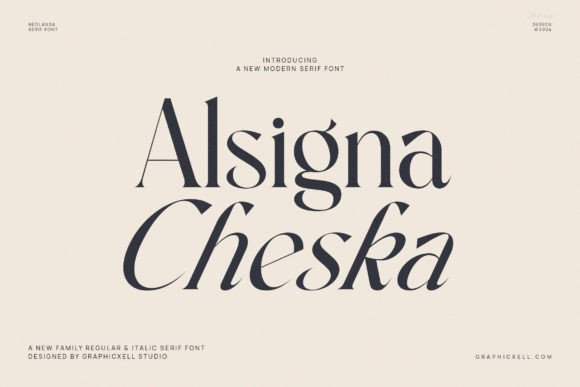
Alsgina Cheska
หากคุณกำลังมองหาเนื้อหาคุณภาพสูงเช่น Alsgina Cheska แพ็คเกจพรีเมียมนี้เป็นตัวเลือกที่ยอดเยี่ยมสำหรับโปรเจ็กต์สร้างสรรค์ของคุณ
ไม่ว่าคุณจะสร้างผลิตภัณฑ์ POD (Print on Demand) คำเชิญงานแต่งงาน หรือกราฟิกโซเชียลมีเดีย Alsgina Cheska ก็เหมาะสมอย่างยิ่ง